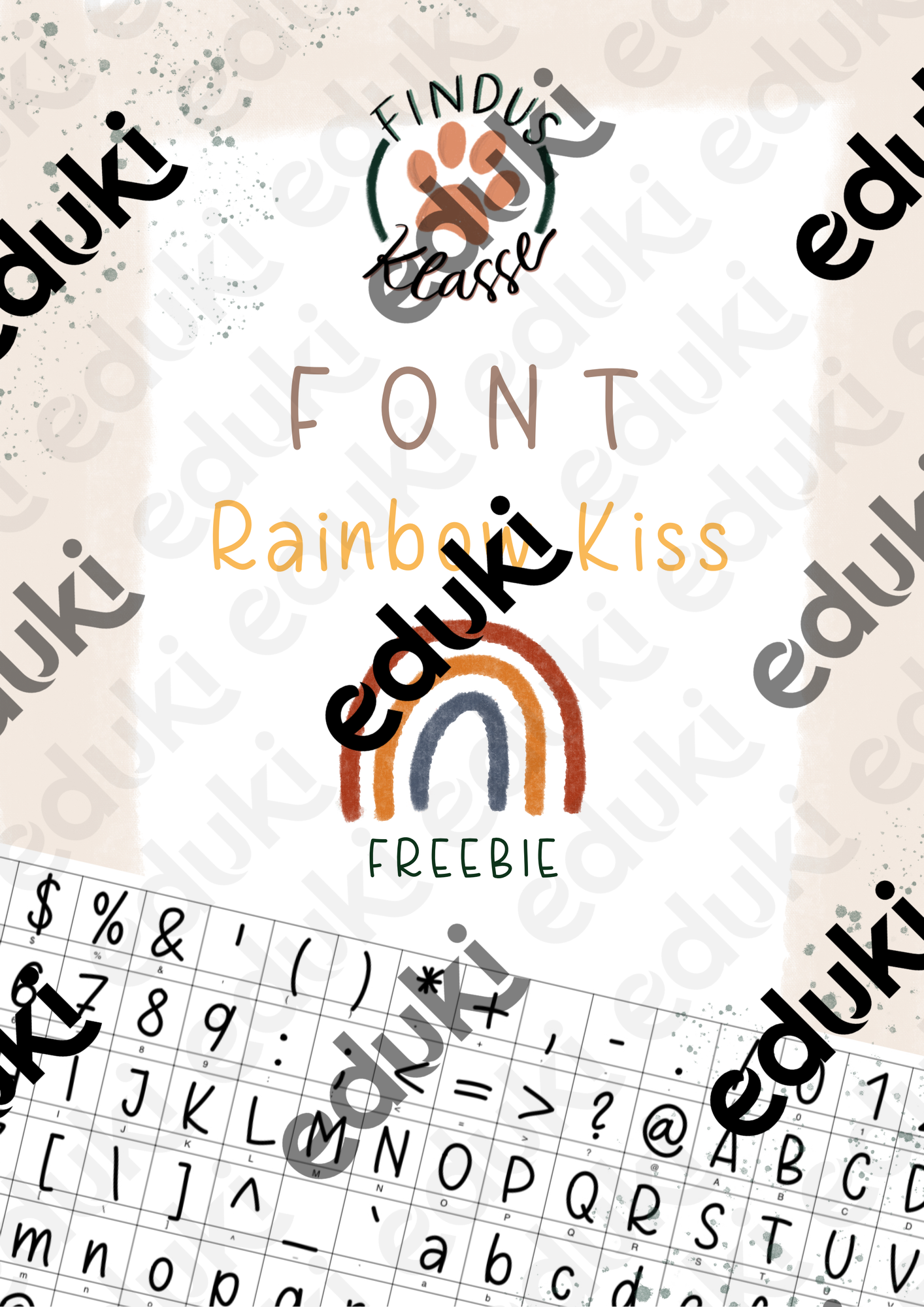
Der Frühling kommt und dazu passend eine Schriftart - Rainbow Kiss! Viel Freude mit der Druckschrift für deine Materialien!
Font Findusklasse Rainbow Kiss I FREEBIE